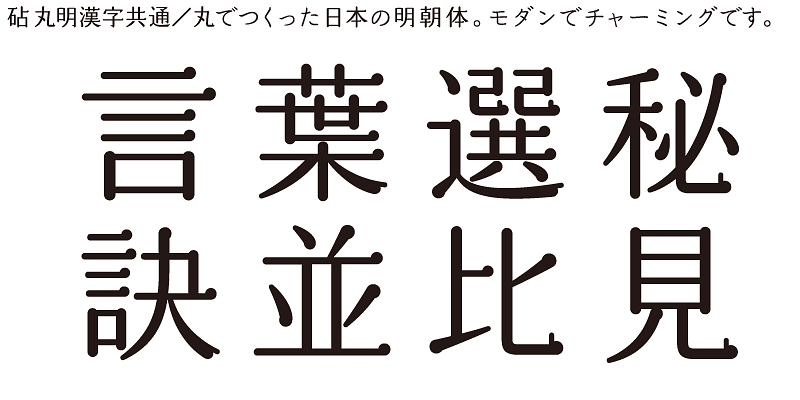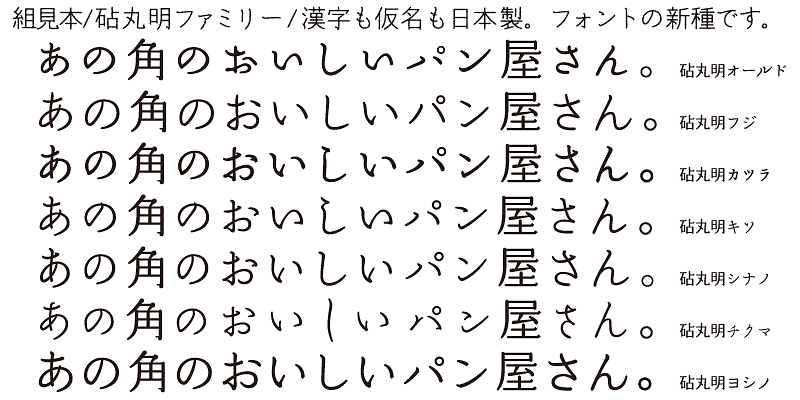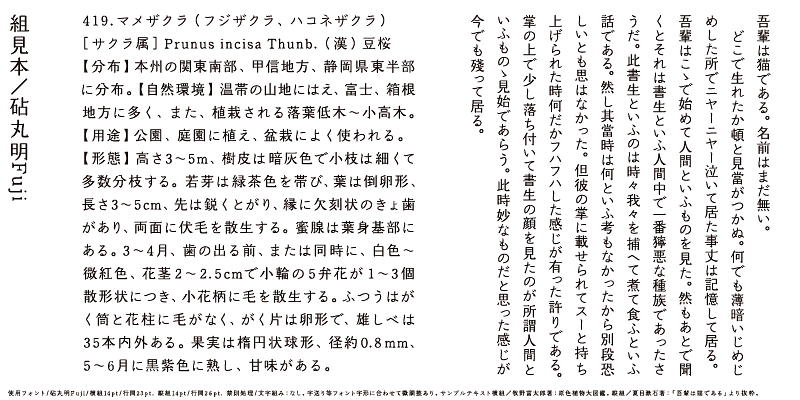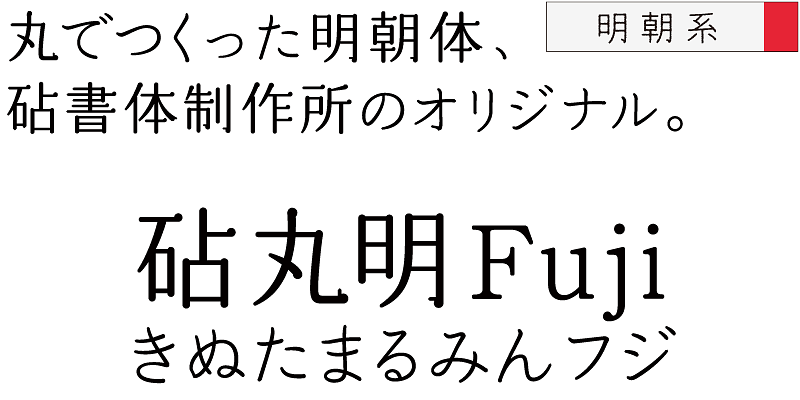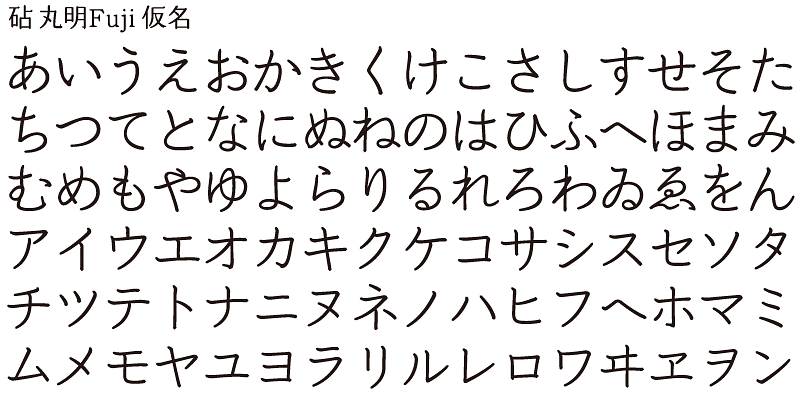
„Orthodox und sanft“ – Die Kana-Zeichen von MaruminFuji sind so gestaltet, dass sie sich etabliert und entspannt anfühlen, mit relativ großen Zwischenräumen und einer überdurchschnittlich großen Zeichengröße, die näher an der von Kanji-Zeichen liegt, so dass sich der Text schön ausrichtet. Die Buchstabenformen vermitteln ein weiches, ruhiges Gefühl. Diese Schriftart kann für eine Vielzahl von Zwecken verwendet werden.
Alle Marumin-Varianten haben die gleichen ideografischen (Kanji-)Zeichen. Das Design der Kanji-Zeichen von Marumin basiert auf dem Mincho-Schriftstil in Japan, hat aber Strichelemente mit abgerundeten Merkmalen. Die Enden der horizontalen und vertikalen Striche, die Punkte sowie die Formen der Tome- und Harai-Striche sind alle abgerundet. Marumin führt eine neue Kategorie von „Rounded Minchotai” mit insgesamt sieben Kana-Varianten ein.
Ein Merkmal der japanischen Sprache sind ihre Kana-Silbenzeichen. Kana-Zeichen wurden in Japan erfunden, um japanische Laute darzustellen und aus China importierte Texte ins Japanische zu übersetzen. Kana-Zeichen werden benötigt, um japanische Wörter und Ausdrücke aus Kanji (chinesischen ideografischen Zeichen) zu erstellen. Auch wenn es Zweideutigkeiten gibt, zeigen diese Wörter und Ausdrücke die Wärme und Sanftheit des Lebens der Menschen, die in dem kleinen und dicht besiedelten Japan leben.
Kinuta Font Factory ist davon überzeugt, dass Kana-Zeichen der Ursprung auf Japanisch geschriebener Wörter sind, und wir glauben, dass die Optimierung von Kana-Zeichen japanische Texte attraktiver macht. Im Durchschnitt bestehen 60 % der japanischen Texte aus Kana-Zeichen – ändert sich die Form dieser Zeichen, verändert das auch das visuelle Erscheinungsbild des Textes. Die Möglichkeiten des typografischen Ausdrucks mit einfachen, dynamischen und kurvenförmigen Kana-Zeichen sind enorm und die Üppigkeit japanischer Texte hängt von Kana-Zeichen ab. Aus diesem Grund bietet Kinuta Font Factory viele Variationen von Kana-Schriftarten an.